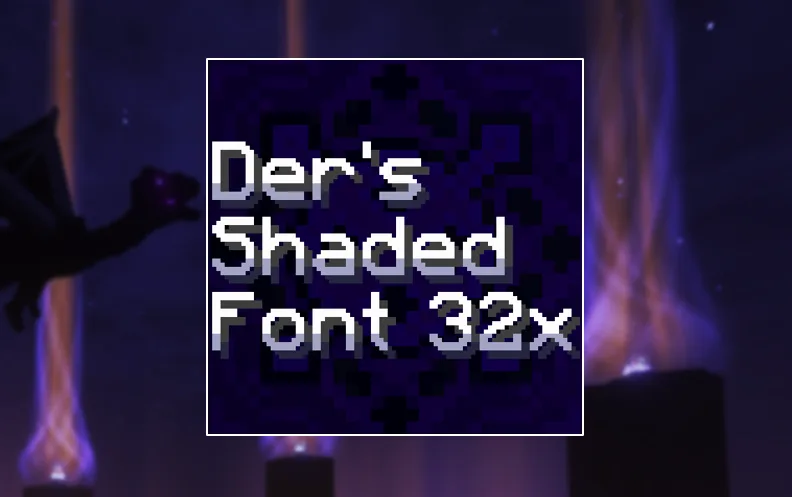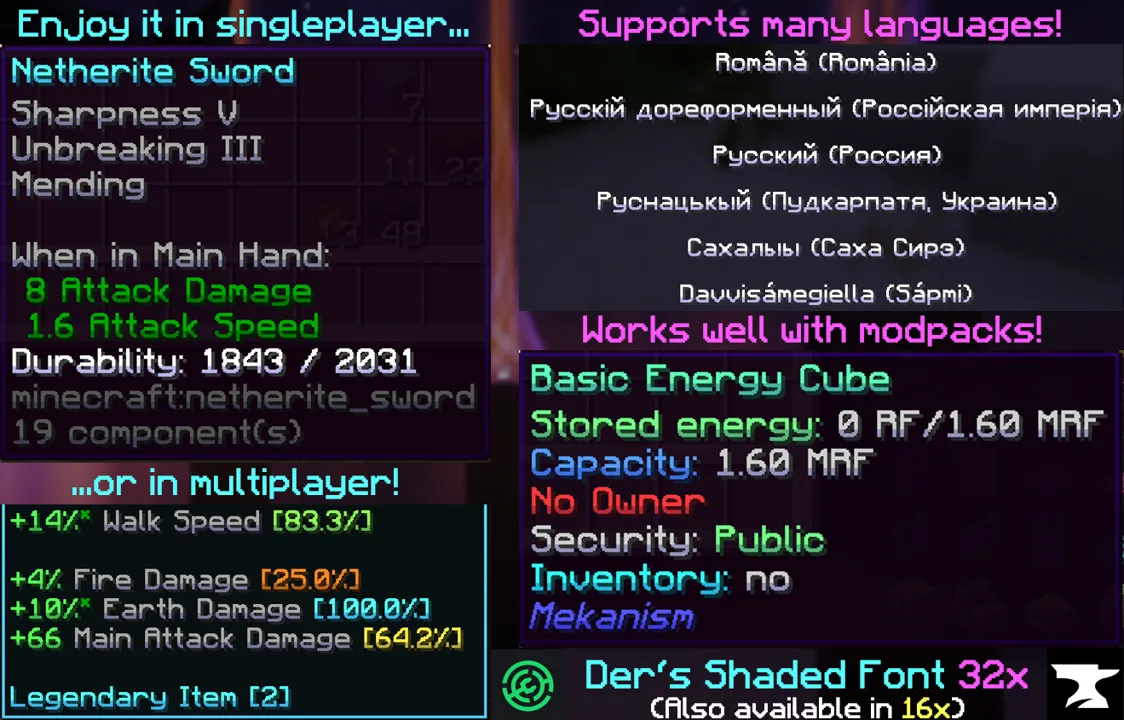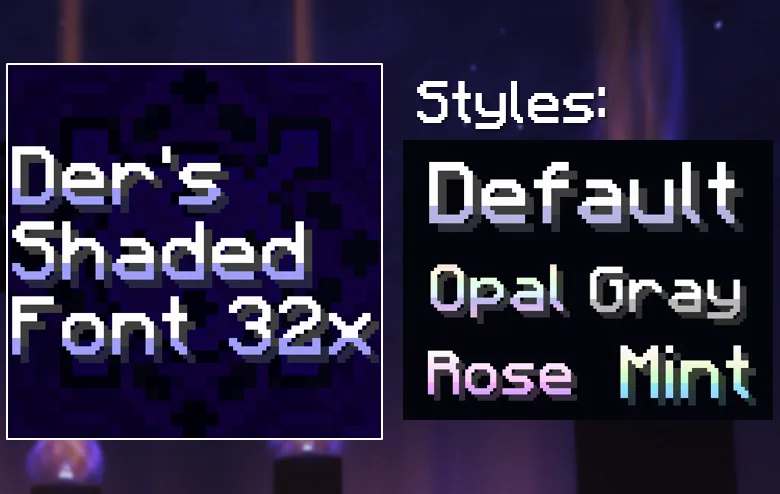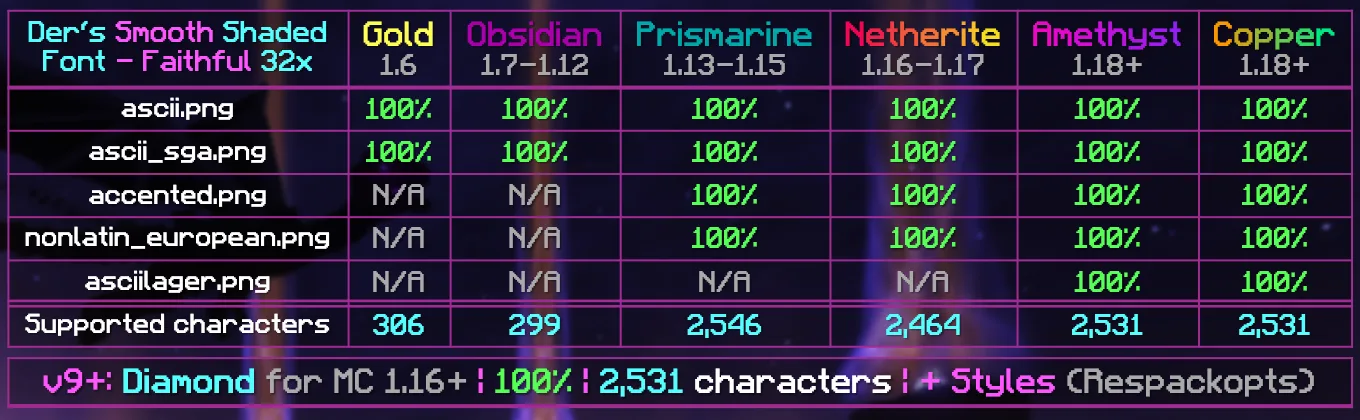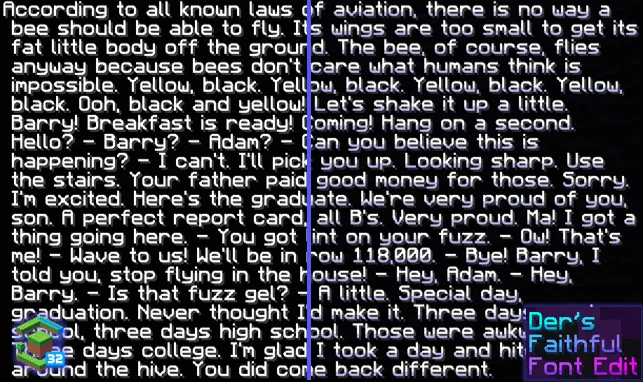
Der's Smooth Shaded Font (Faithful 32x)
Ресурспак модифицирует шрифт Faithful 32x, добавляя цветное затенение к нижним частям символов для более свежего визуального вида. Поддерживает более 11 000 символов, различные языки и широкий диапазон версий Minecraft.
Этот ресурспак изменяет шрифт Faithful 32x, добавляя целенаправленное цветное затенение к нижним частям символов, что придаёт игре более освежающий и визуально привлекательный вид. Поддерживается более 11 000 символов, включая различные языки, множество символов и широкий диапазон версий игры.
Включает все шрифты Faithful 32x с затенением: основные символы, стандартный галактический алфавит для зачарования, специальные символы, акцентированные буквы и нелатинские европейские символы. Последние версии добавили более 8 500 затенённых глифов на 37 страницах Юникода, расширенную поддержку языков и символов, а также исправления ошибок ширины глифов в ванильной версии.
Ранее существовали различные стили затенения и редакции для группировки версий игры, но начиная с версии v10 используется единый файл для Minecraft 1.16+ без множества стилей затенения и необходимости в модах.